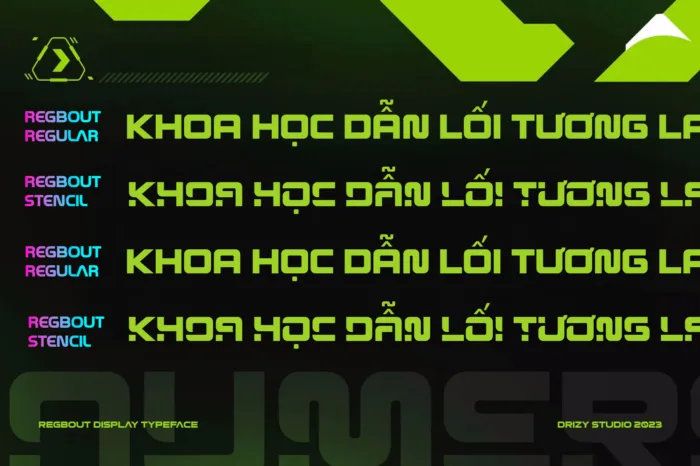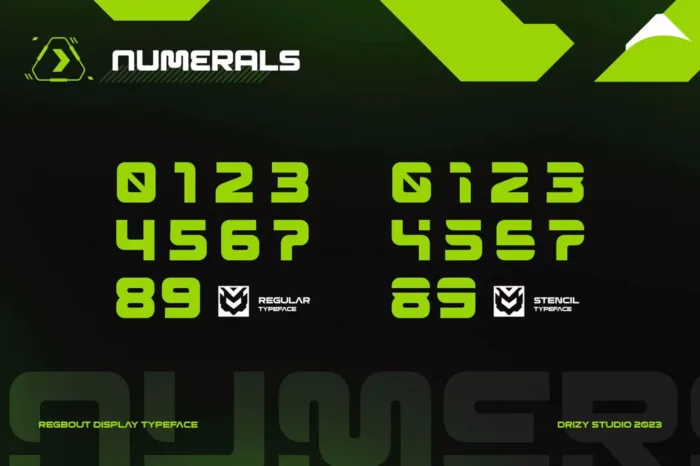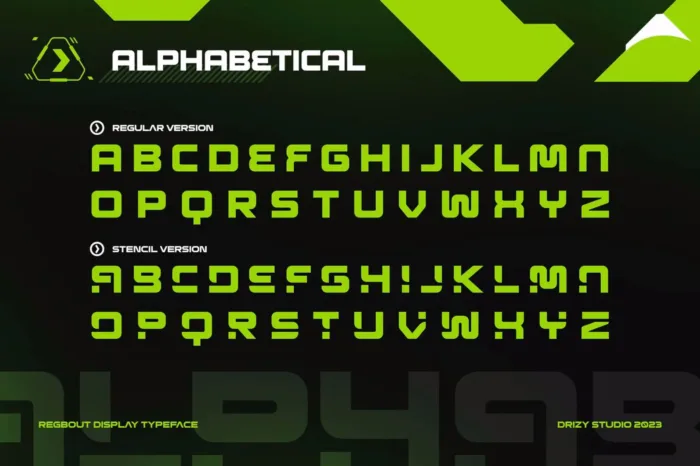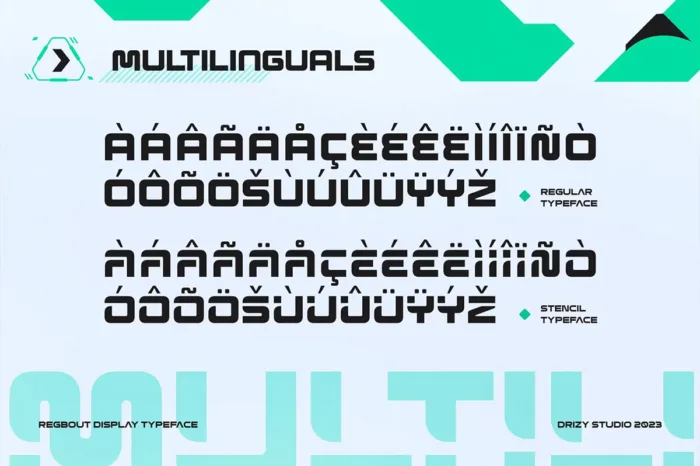
DVN Regbout Việt hóa – Font chữ Logo phong cách công nghệ, tương lai (2 Style)
“Regbout” là một phông chữ stencil hiện đại và bóng bẩy được thiết kế cho tính thẩm mỹ tương lai. Với các đường nét gọn gàng và thiết kế tối giản, mỗi ký tự đều toát lên phong cách đương đại và sự đổi mới. Hoàn hảo cho các logo bóng bẩy, thiết kế lấy cảm hứng từ công nghệ và các dự án theo chủ đề đô thị, “Regbout” mang đến diện mạo táo bạo và đặc biệt, đảm bảo thông điệp của bạn được truyền tải với một chút phong cách tương lai và tác động trực quan.
Phiên bản Việt hóa bao gồm 2 Style: Regular (phiên bản bình thường) và Stecil (phiên bản nét đứt)